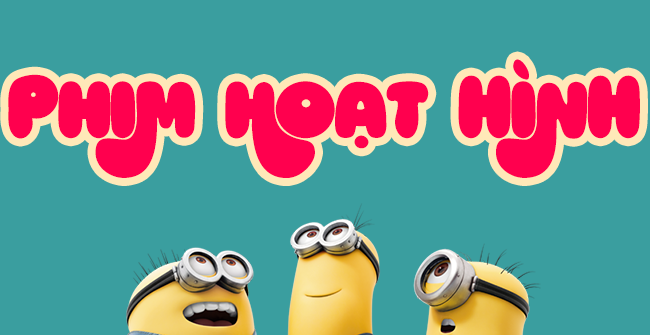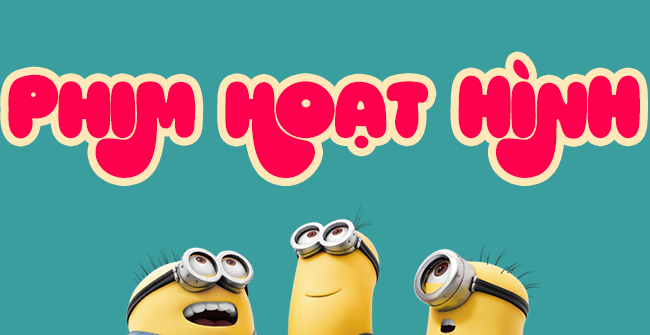
Tác giả: Ricardo Marcin & Erica Jung
Phân loại: Đa dạng màu sắc
Font SVN Ziclets là kiểu chữ thuộc bộ font SVN sáng tạo, vui nhộn và đầy màu sắc, thường được ưa chuộng trong các thiết kế hướng đến trẻ em hoặc các dự án cần sự tươi mới và năng động. Với các đường nét mềm mại, phá cách, SVN Ziclets mang đến cảm giác trẻ trung, sôi động và giàu tính thẩm mỹ. Phông chữ này hoàn hảo cho các ấn phẩm quảng cáo, poster, bao bì sản phẩm hoặc các dự án sáng tạo cần tạo sự nổi bật. Font SVN Ziclets không chỉ dễ nhìn mà còn giúp truyền tải thông điệp một cách thân thiện và cuốn hút.